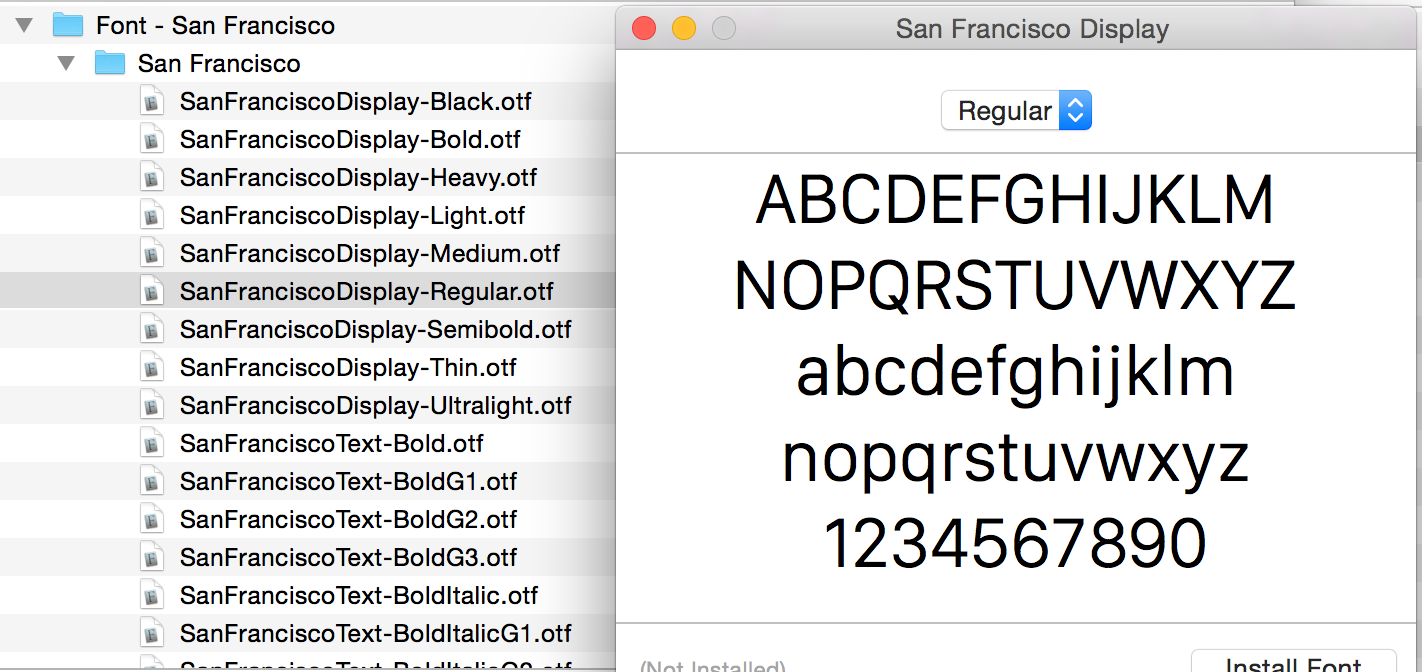
Welche Schriftart wird denn bei  WATCH verwendet?
Oder ist’s gar ein handgebissenes Logo?
Das ist die von R::bert schon angesprochene Interface-Schrift der Uhr selber.
Momentan immer noch ein ziemliches Durcheinander mit der Myriad, der Helvetica (iOS) und nun der »Codename: Apple Sans« auf der WATCH.
Ähnliche Fonts: Akkurat, Brix Sans, JAF Facit, Nitti Grotesk, Real
Kann ich mir nicht vorstellen. Ich dachte es geht um Exklusivität – gerade bei den Uhren.
An der Stelle von Apple hätte ich mir tatsächlich mal die Akkurat näher angesehen. Passt formal zu den Produkten und ist als Schweizer Nachfolger der Helvetica doch geradezu prädestiniert dazu eine »Uhren-Font« zu sein. ;-) Außerdem wirkt sie noch etwas »wärmer« und charakterstärker und könnte so die eigene visuelle Identität stärken. Diese dann entsprechend der Bedürfnisse von Apple anzupassen und auszubauen dürfte ja nicht das Problem sein.
Aber sollte man den Apple-Geräten willentlich einen der Android-Schrift so ähnlichen Font geben?
neee. das steht auch außer diskussion.
apple braucht ’ne ordentliche hausschrift und muss weg vom helvetica-myriad-roboto-brei.
Och, die Myriad macht sich doch gar nicht so schlecht, wie ich finde und hat die visuelle Identität von Apple sehr geprägt. Aber vielleicht wollen sie originell wirken und verzichten deshalb auf deren konsistenten Einsatz. ;-)
Was würde Euch denn so vorschweben?
naja, nix was andere auch nutzen können. 'ne richtige hausschrift,
zeitlos und mit charakter. gern in richtung akkurat, myriad hat doch jeder auf dem rechner.
Und trotzdem wissen diese nur wenige so gekonnt einzusetzen wie Apple.
Und vermittelt nicht gerade diese Verfügbarkeit ein Gefühl Teil des Ganzen oder zumindest nicht vom elitären Kreis der Markenwelt ausgeschlossen zu sein. Ich finde das aus Apple-Sicht gar nicht so dumm, dass die Myriad so verbreitet ist. Eher, dass andere wie Microsoft auf diesen Zug aufgesprungen sind.
Tataa! Die neue Apple-Schrift … heißt Sans Francisco.
Ich wusste gar nicht, das Univers und DIN* sooo eng befreundet sind. ;-)
*Die DIN hat übrigens auch schon ’ne Weile in der iOS-Kamera-App geparkt …
Dein Rechtschreibfehler "Sans Francisco" wäre eigentlich ein schöner Name für den neuen Uhrenfont. Dazu noch eine passende Serif Francisco … :-)